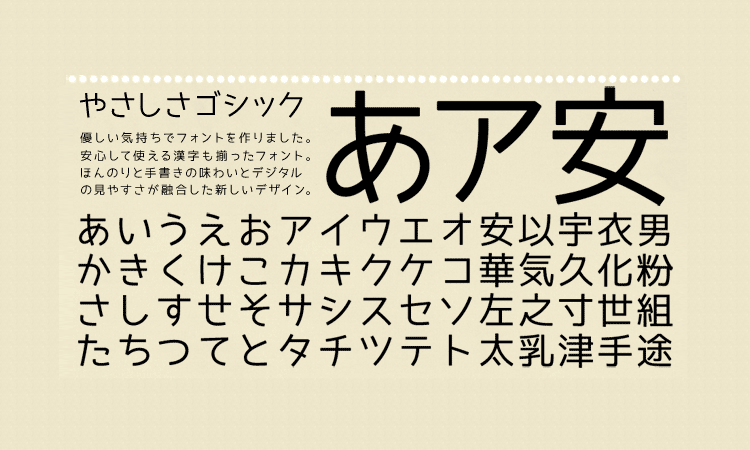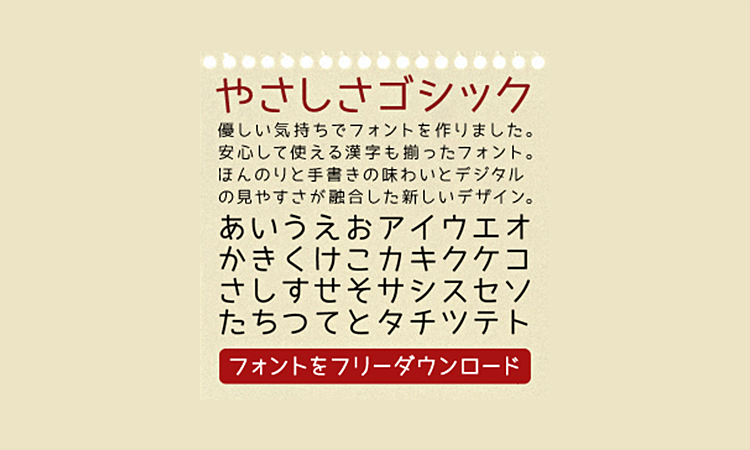
やさしさゴシックは、やさしい印象のゴシック体フォントです。少しだけ手書きの味わいがあります。可読性が高く、Webなどデジタルでの使用に向いています。漢字は第二水準文字まで揃っており、安心して使うことができます。数字、アルファベット、記号、かな文字(ひらがな・かたかな)、教育漢字、常用漢字、第一水準漢字、第二水準漢が収録されています。
同じシリーズに、少し太字にしたやさしさゴシックボールドがあります。